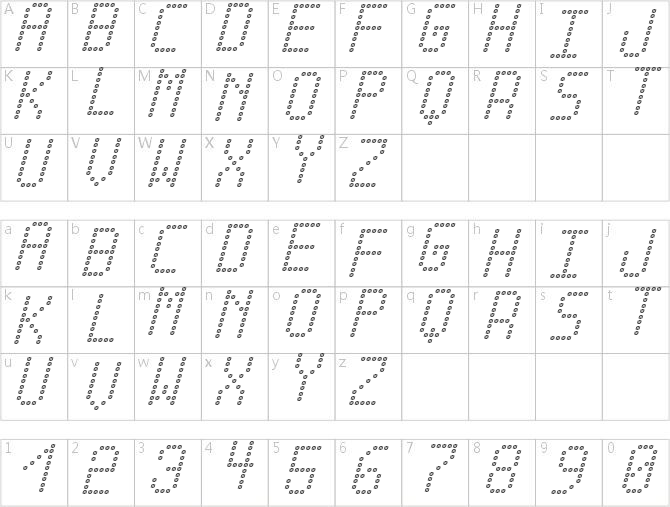
Cross-led-tfb-Italic 詳情頁
Cross-led-tfb-Italic字體字庫是一款讓人賞心悅目、百看不厭的英文字體,適合各類廣告和產(chǎn)品包裝設(shè)計應(yīng)用,字體大小0.09MB,格式為ttf字體,上傳用戶是yinjun,作者/版權(quán)方為未知